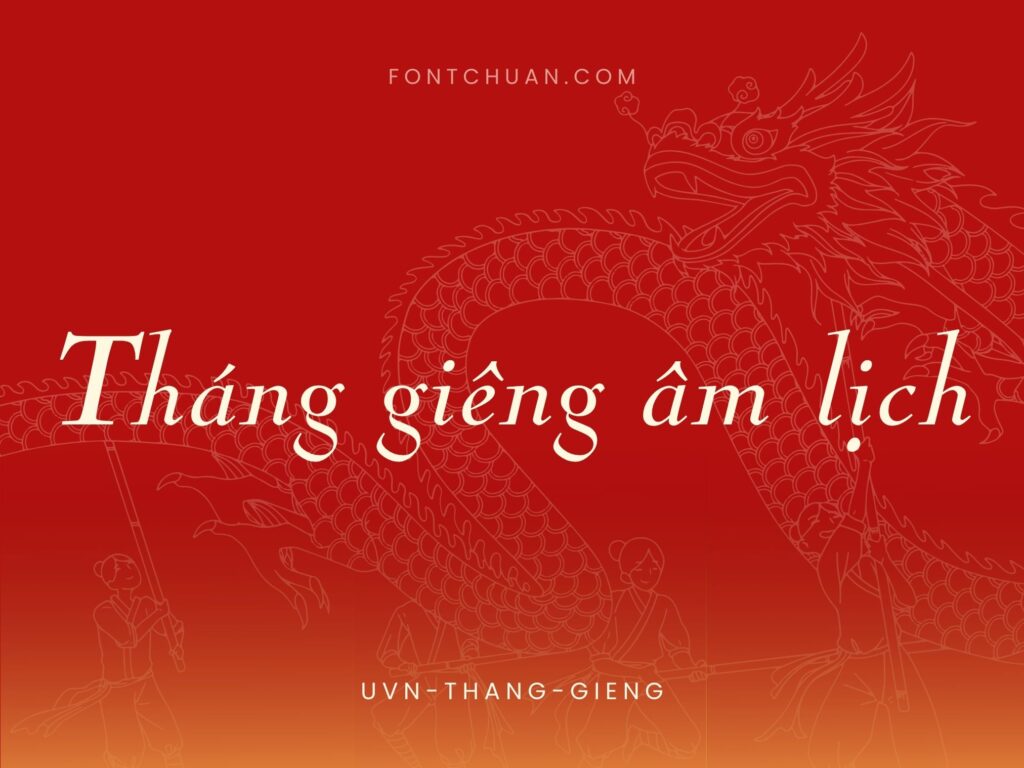
Font UVN Thang Gieng Việt Hóa
UVN Tháng Giêng là một kiểu chữ script mang phong cách viết tay mềm mại và tự nhiên, tạo cảm giác thân thiện và gần gũi. Font này chỉ được sưu tầm và đăng bởi thành viên của Font Chuẩn.
UVN Tháng Giêng có cấu trúc chữ với các nét thanh mảnh và độ nghiêng nhẹ, phù hợp cho các ứng dụng như thiết kế thiệp mời, tiêu đề, logo và các ấn phẩm in ấn yêu cầu sự tinh tế và nghệ thuật. Các ngành nghề như quảng cáo, giáo dục, công nghệ và bất động sản có thể tận dụng UVN Tháng Giêng để tạo điểm nhấn độc đáo trong thiết kế.